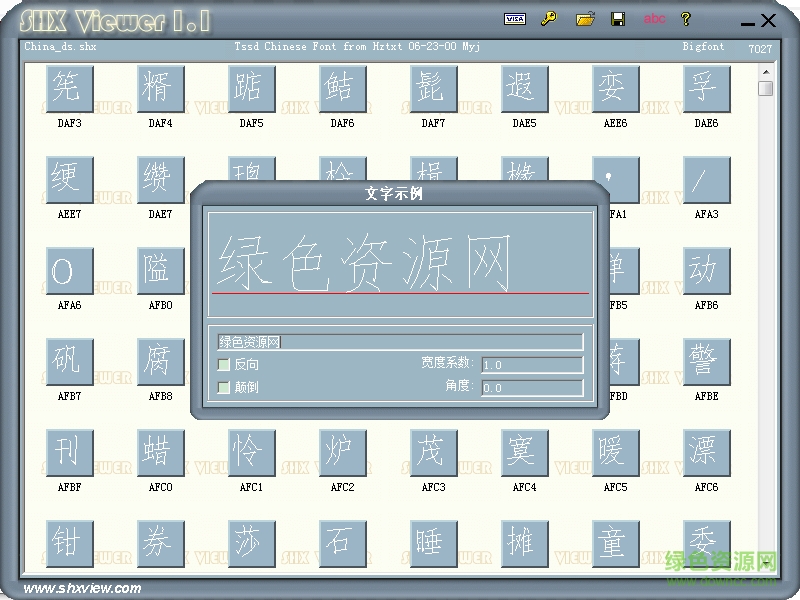
china ds.shx字體
chinads.shxautocad中必不可少的一款字體,用戶一般在設(shè)計(jì)圖紙中經(jīng)常用到此款字體,該字體結(jié)構(gòu)簡(jiǎn)潔字型清晰易讀,缺少該字體會(huì)導(dǎo)致頁(yè)面亂碼無(wú)法顯示,需要的朋友歡迎來(lái)綠色資源網(wǎng)下載!
china ds.shx字體